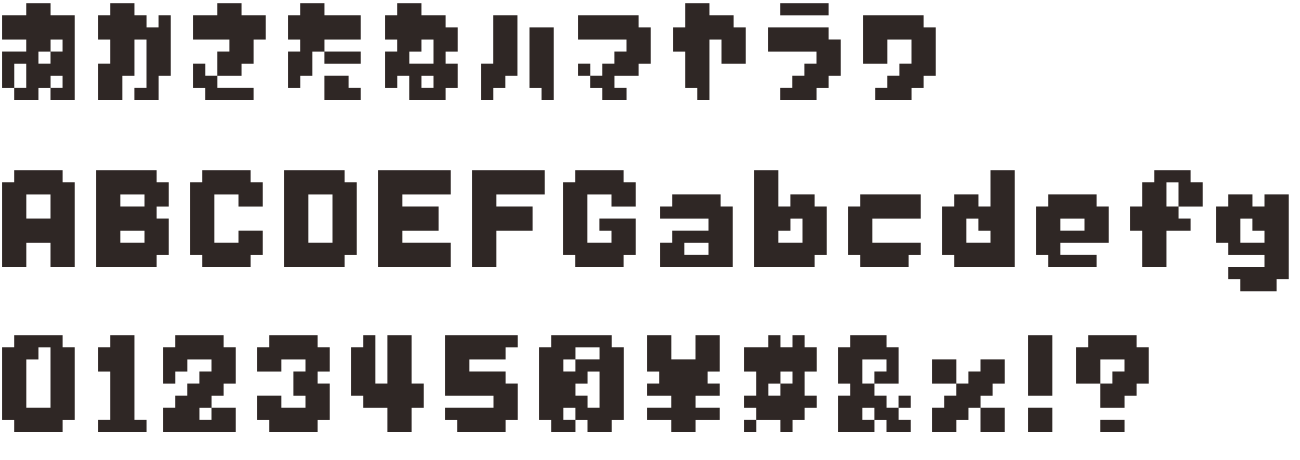
よこはまドット
ドットの大小を自由に調整できる、太めでレトロかわいいバリアブルのピクセルフォント。CSSで可変可能なWebフォント用データも同梱されています。
よこはまドット Dot50
よこはまドット Dot75
よこはまドット Dot100
よこはまドット Dot125
よこはまドット Dot150
よこはまドット Dot175
よこはまドット Dot200